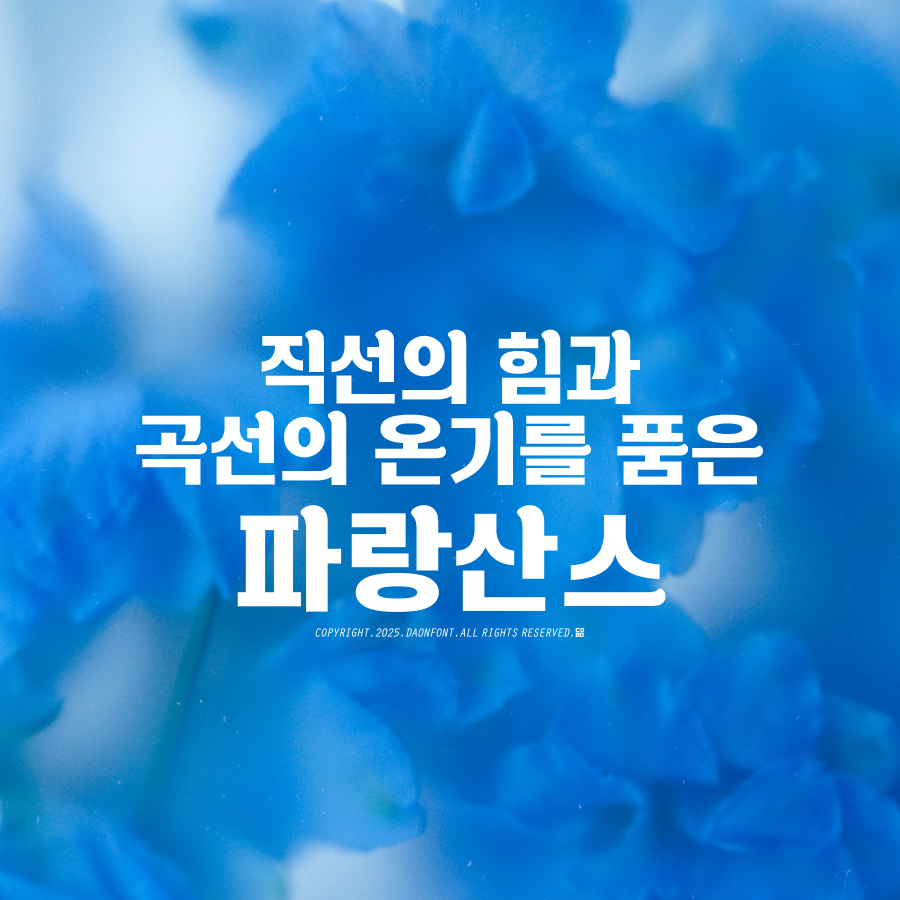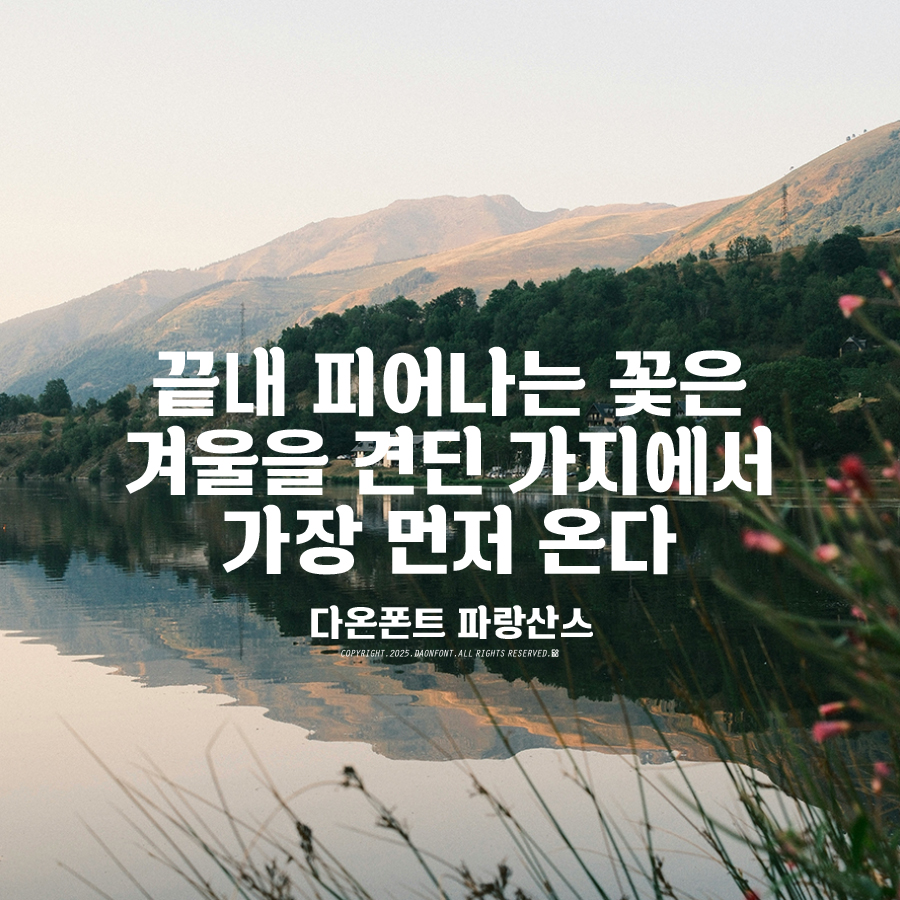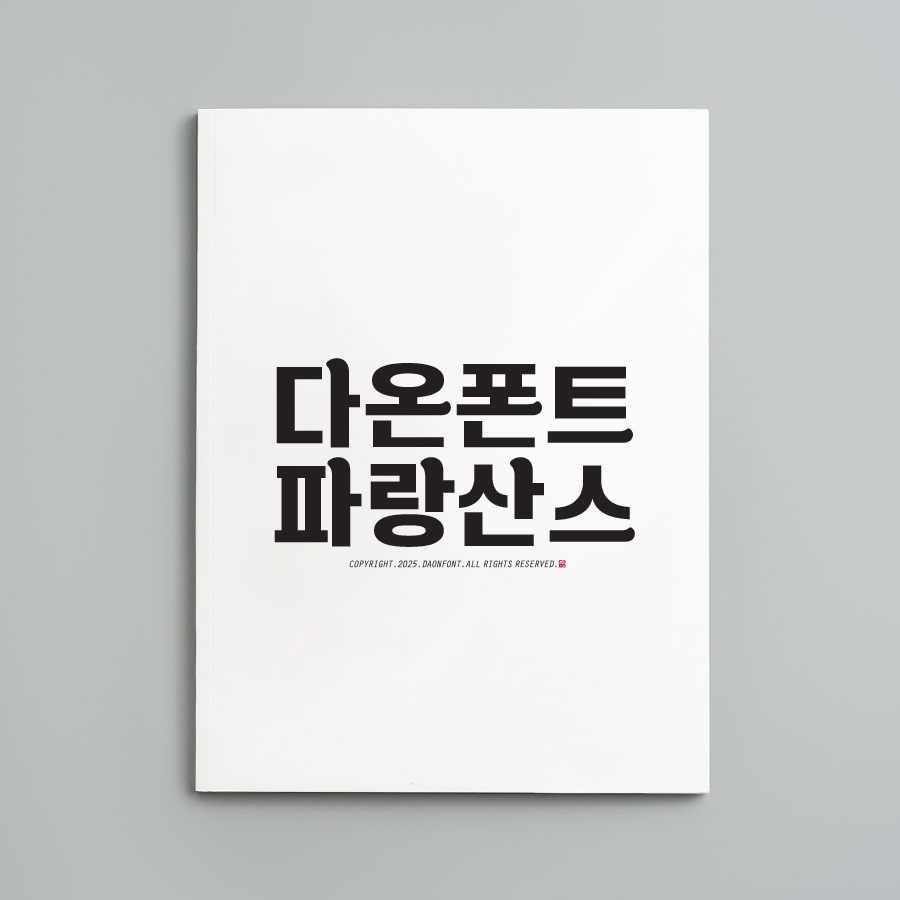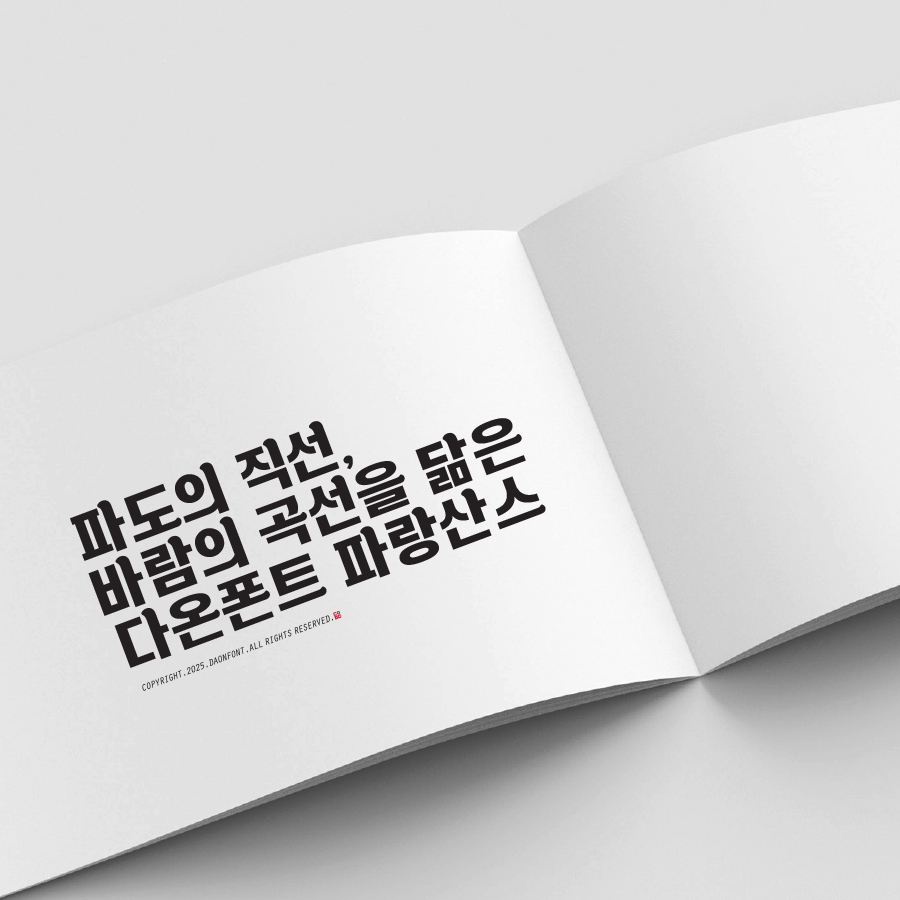
다온폰트의 새로운 헤드라인 서체, 파랑산스가 출시됩니다.
직선의 힘과 곡선의 온기를 담다.
다온폰트의 새로운 헤드라인 서체, 파랑산스가 출시됩니다.
묵직한 직선은 강렬한 인상을 전하고,
부드러운 곡선은 따뜻한 여운을 남깁니다.
파랑산스는 한눈에 시선을 사로잡는
강렬한 헤드라인 전용 산세리프 서체입니다.